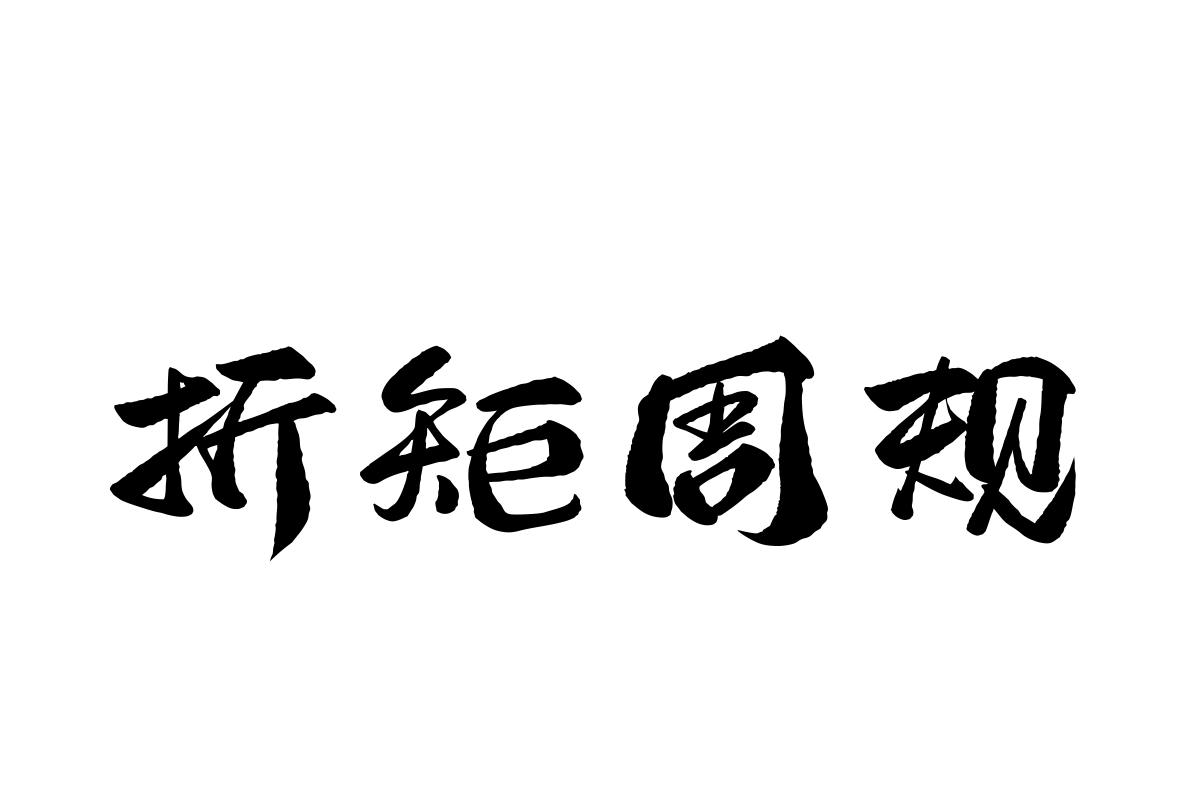
汉仪二码古风字体是一款具有浓厚中国古典韵味的书法字体,它以简洁明快的风格和优雅流畅的笔画线条,展现出了中国传统文化的独特魅力。这款字体在设计上注重细节,线条流畅自然,结构紧凑而不失灵动,给人一种古朴典雅的感觉。
汉仪二码古风字体适用于各种需要展现中国传统文化元素的场合,如书籍、杂志、广告、包装等。它的应用范围广泛,无论是用于文字排版还是作为图形元素,都能为作品增添一份古典之美。
汉仪二码古风